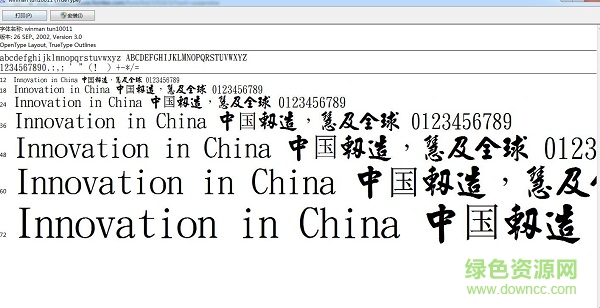
winman tun10011字體
金梅毛行書國(guó)際碼(winman tun10011)是一款漂亮的行書字體,線若游絲,流暢大氣,藝術(shù)性高,適用于影視海報(bào)設(shè)計(jì)、書籍封面等領(lǐng)域,喜歡的朋友快來綠色資源網(wǎng)下載吧!
行書字體介紹
行書是楷書的快寫,相傳始于漢末。它不及楷書的工整,也沒有草書的草率。每個(gè)字呈現(xiàn)大小不同,存在著一個(gè)字的筆與筆相連,字與字之間的連帶,既有實(shí)連,也有意連,有斷有連,顧盼呼應(yīng)。
金梅毛行書國(guó)際碼